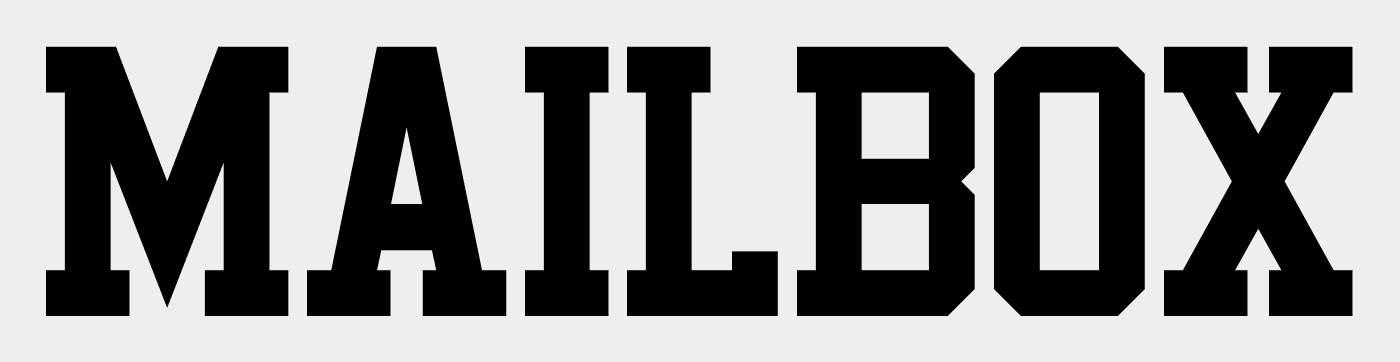
Welche schriftart ist unser Band-logo?
Folgendes Problem:
Wir haben vor ca 2 Jahren eine Band gegründet...
Und uns dazu von einem Bekannten ein Logo erstellen lassen,
dieser weiß aber leider selbst nicht mehr welche Schriftart er verwendet hat.
Da wir jetzt auf nachfrage einiger Fans Merchendise erstellen wollen
wäre es nicht schlecht die Schriftart zu kennen..
Da gibt es tausende, die sich nur marginal unterscheiden. Jene ist nahe dran:
Es gibt aber auch viele kostenfreie Fonts dieser Art. Und das Logo ist in zwei Minuten nachgebaut …
Soweit waren wir auch schon.. aber es geht um die Verbingungen zwischen den Buchstaben und dieses leicht angeschrägte...
die „verbindungen“ sind gar keine, sondern sind einfach verringerte abstände.
die schräge entsteht durch das scheren, also verzerren jedes einzelnen buchstabens mit gleichem winkel.